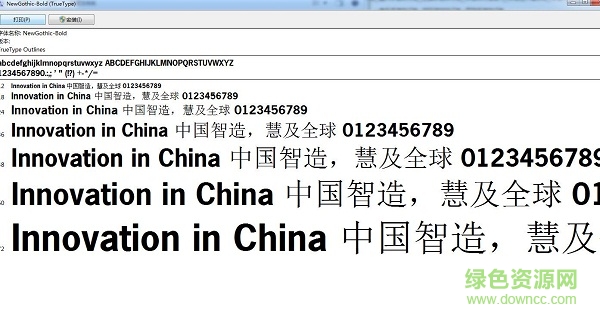
newsgothicbt字體包收錄了newsgothicbt-bold粗體、newsgothicbt-light細體以及newsgothicbt-romancondensed等多款字體,字形端正大方,適用于海報、期刊等領域,喜歡的朋友快來下載吧!
1.字體筆畫的曲直走向賦予了字體力量和彈性。
2.直線是峭壁、落石、參天古木,或是茫茫平野、千里陣云,直來直往的線條代表了坦蕩、干脆、果敢,但也可能意味著死板與偏執(zhí)。
3.直線賦予字體的是一種陽剛的氣質(zhì),那么曲線就代表了陰柔的一面,曲線是柔絲、浮云、蒲柳,是九曲回腸,更多了一分包容與婉轉(zhuǎn)。